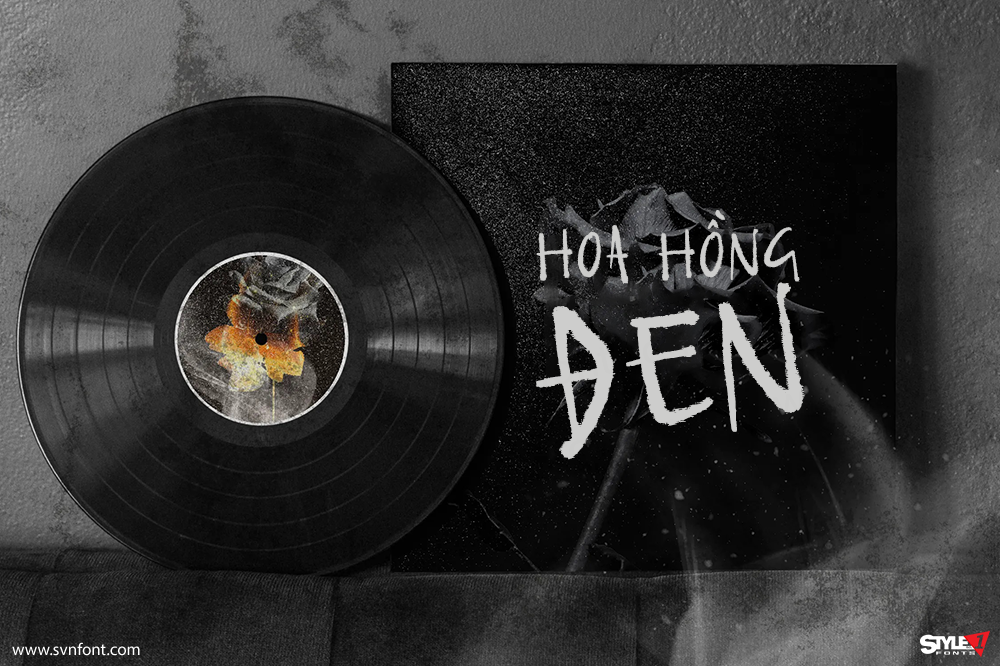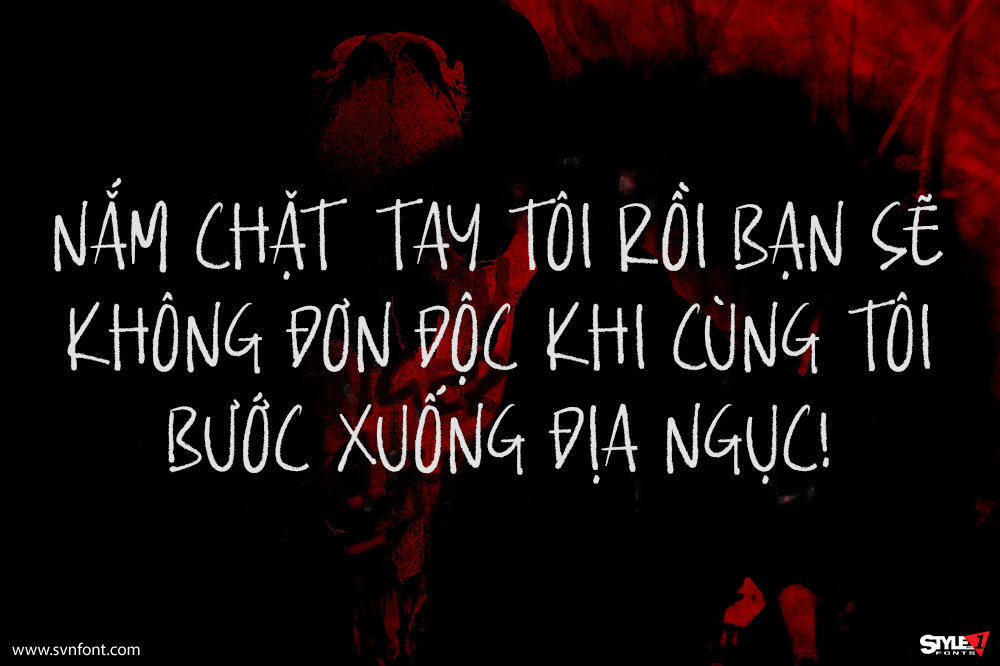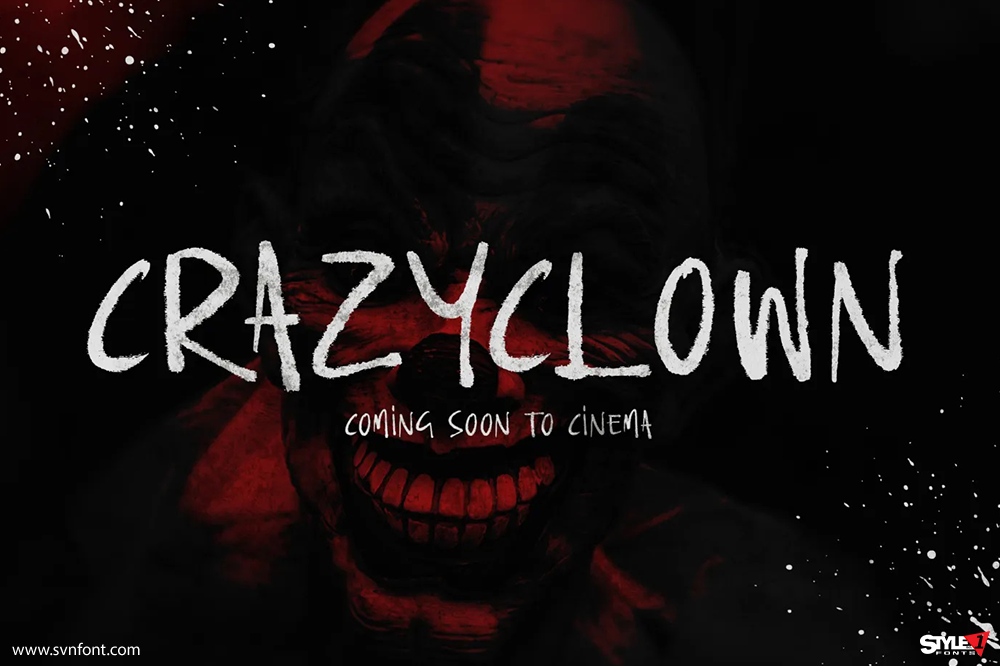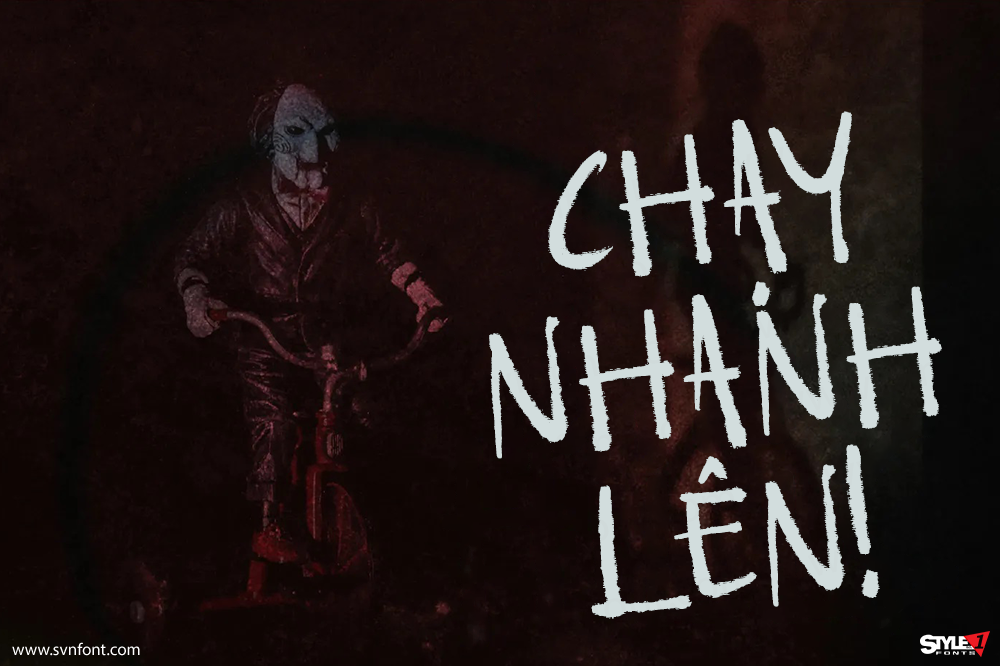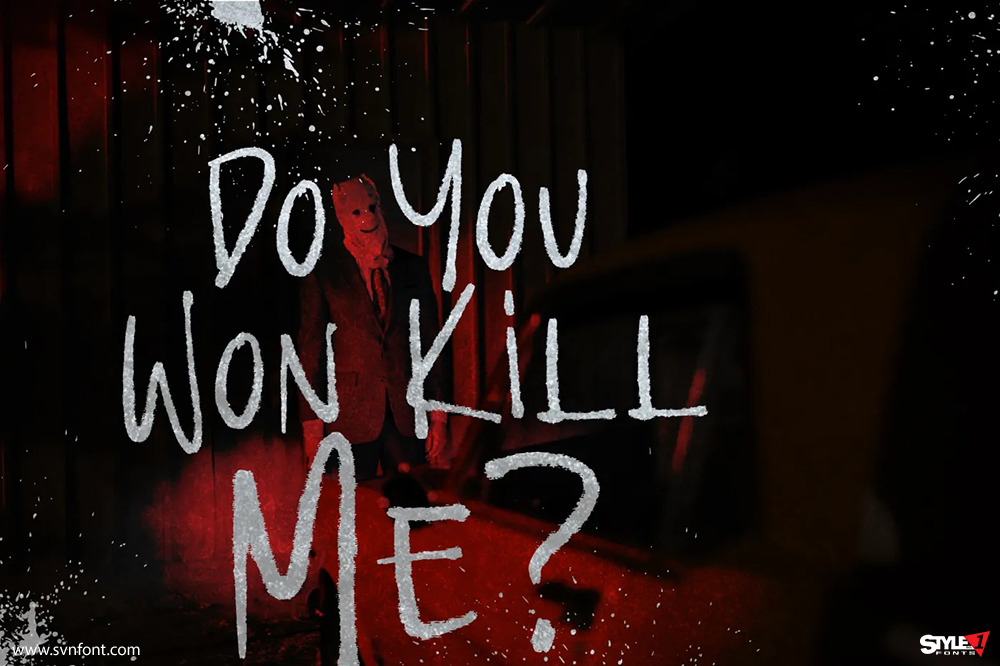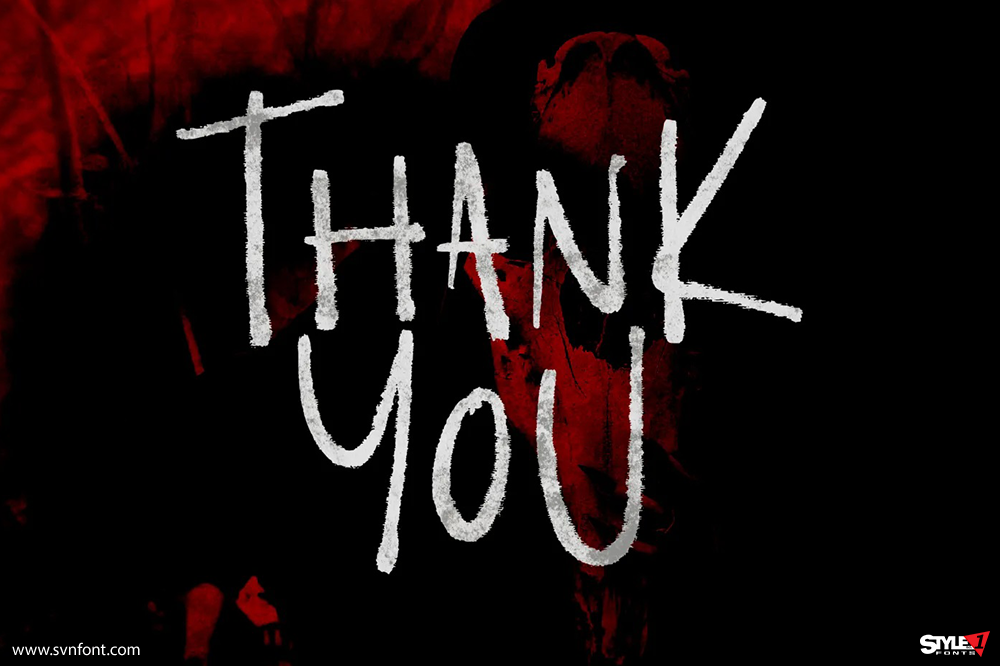
Vampires là font brush phong cách kinh dị đến từ Glorytype Studio, phù hợp cho nhiều dự án sáng tạo như logo, branding, đồ gia dụng, bao bì sản phẩm, ly cốc, câu trích dẫn, poster, túi mua sắm, áo thun, bìa sách, danh thiếp, thiệp mời, thiệp chúc mừng, nhãn mác, nhiếp ảnh, watermark, các sự kiện đặc biệt và mọi dự án cần chất script độc đáo, ấn tượng và đầy cảm xúc.
Nhà thiết kế: Glorytype
Nhà phát hành: Glorytype